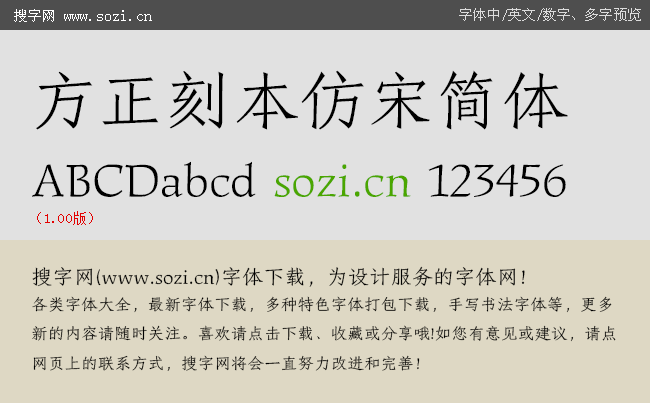
方正刻本仿宋簡(jiǎn)體
搜字網(wǎng)提供一款方正刻本仿宋簡(jiǎn)體中文字體下載,方正刻本仿宋采用刻本筆畫風(fēng)格,刻本仿宋整體結(jié)構(gòu)效仿傳統(tǒng)仿宋,不同的是,刻本仿宋的橫劃不及傳統(tǒng)仿宋那么陡峭,因此字面調(diào)整的更為方正;其次,傳統(tǒng)仿宋的寫法有的布白不夠舒服,刻本仿宋參考楷書的寫法做了相應(yīng)調(diào)整。適合畫冊(cè)排版、報(bào)紙排版、網(wǎng)頁(yè)設(shè)計(jì)等廣告設(shè)計(jì)。